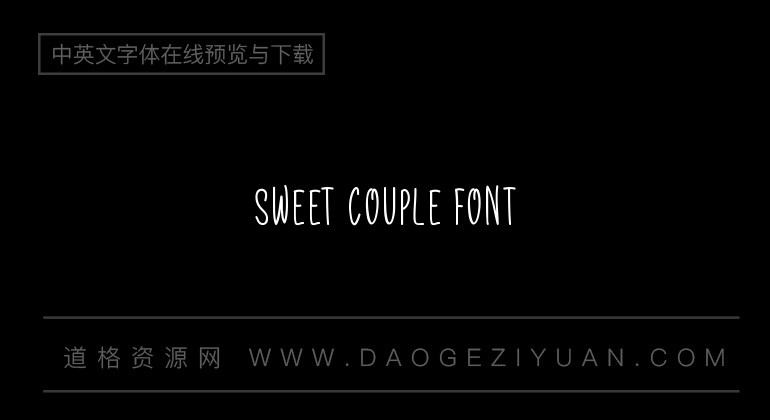
Sweet Couple Font
Sweet Couple Font 是一种手写风格的字体,适合用于设计浪漫、甜蜜、温馨的场合,比如婚礼、情人节、生日等庆祝活动。这款字体的特点是字母间距较为紧密,线条柔和流畅,符号和装饰元素较多,能够为设计增添一份温柔的气息。此外,Sweet Couple Font 还提供了多种字型和颜色选择,方便使用者根据设计需要进行调整。无论是在印刷品、海报、贺卡、网页等方面,Sweet Couple Font 都能够为你的作品带来独特而又浪漫的效果。
Sweet Couple Font是一款非常不错的手写艺术字体,具有很好的视觉感,适合于文化类的宣传设计、商业类品牌的广告和产品包装设计以及个性化文字排版等较多场景。